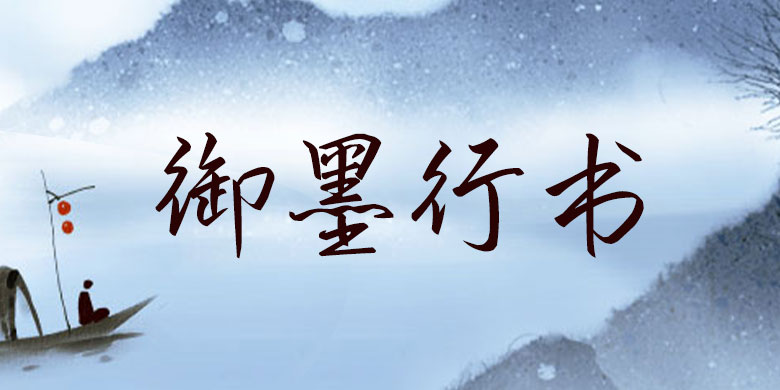
品牌:方正手迹设计师:尚正中发行时间:2019字库编码:大陆简体(GB2312-80)分类:常规书写·硬笔字体属性:精品字
御墨行书这款字体用笔从容不迫,不疾不徐,起承转合,自然随意,字势宽博,重心平稳,韵味悠长。适用于文艺类的书刊、文化类宣传设计、综艺字幕、品牌广告和产品包装设计,以及社交网络的个性化用字。